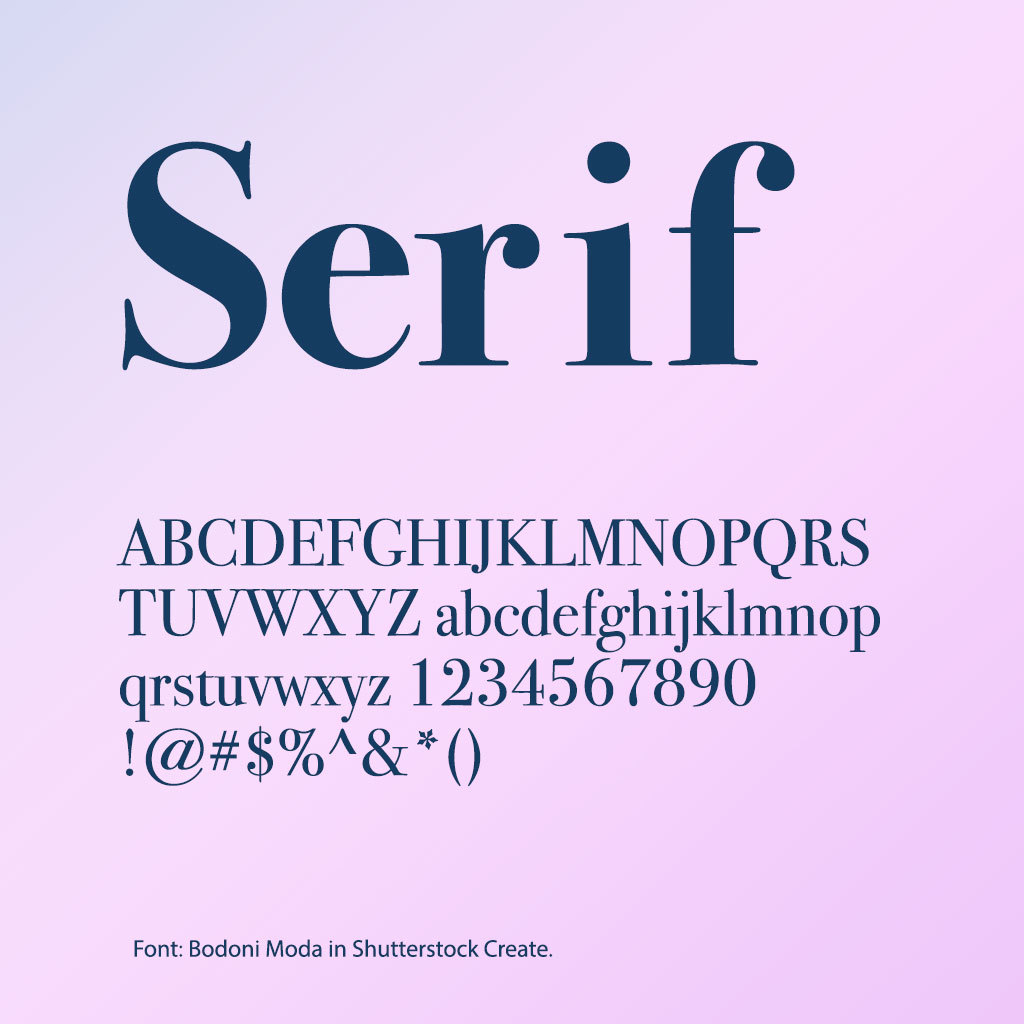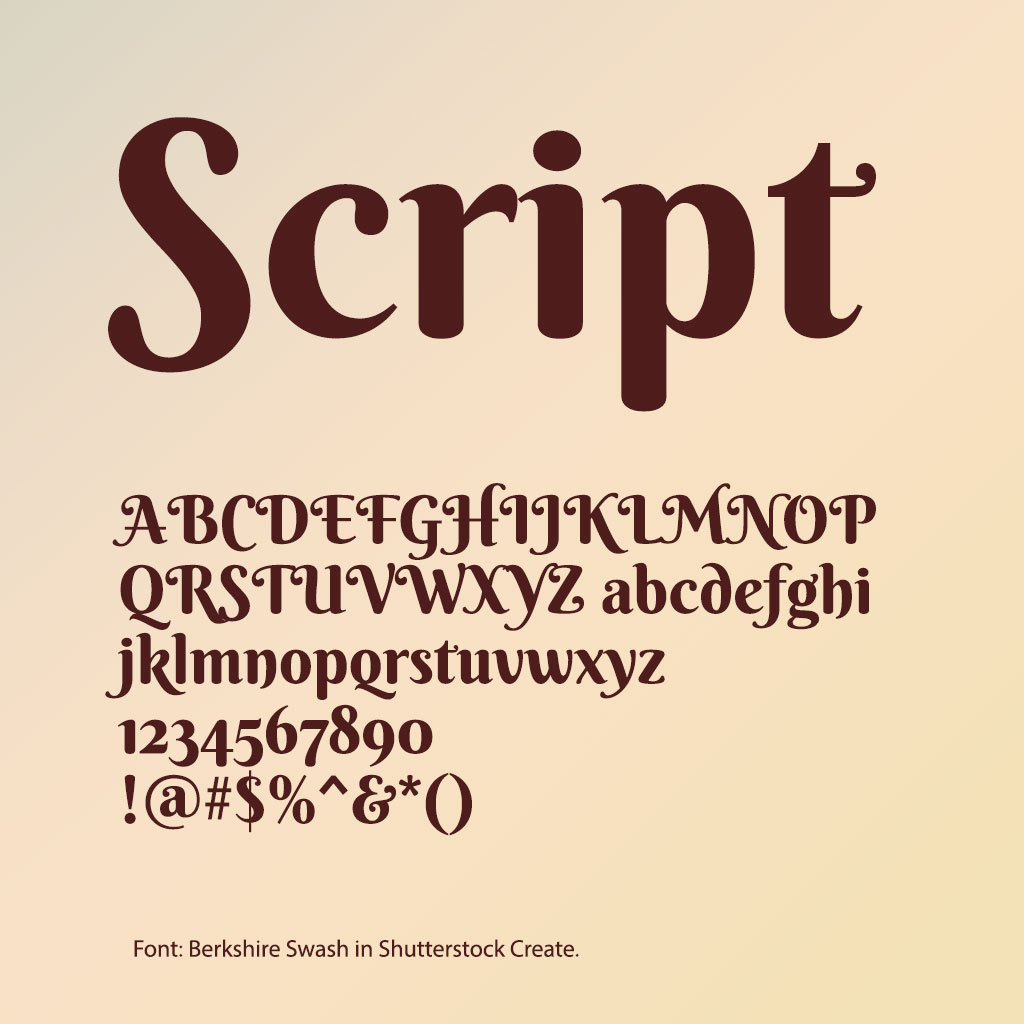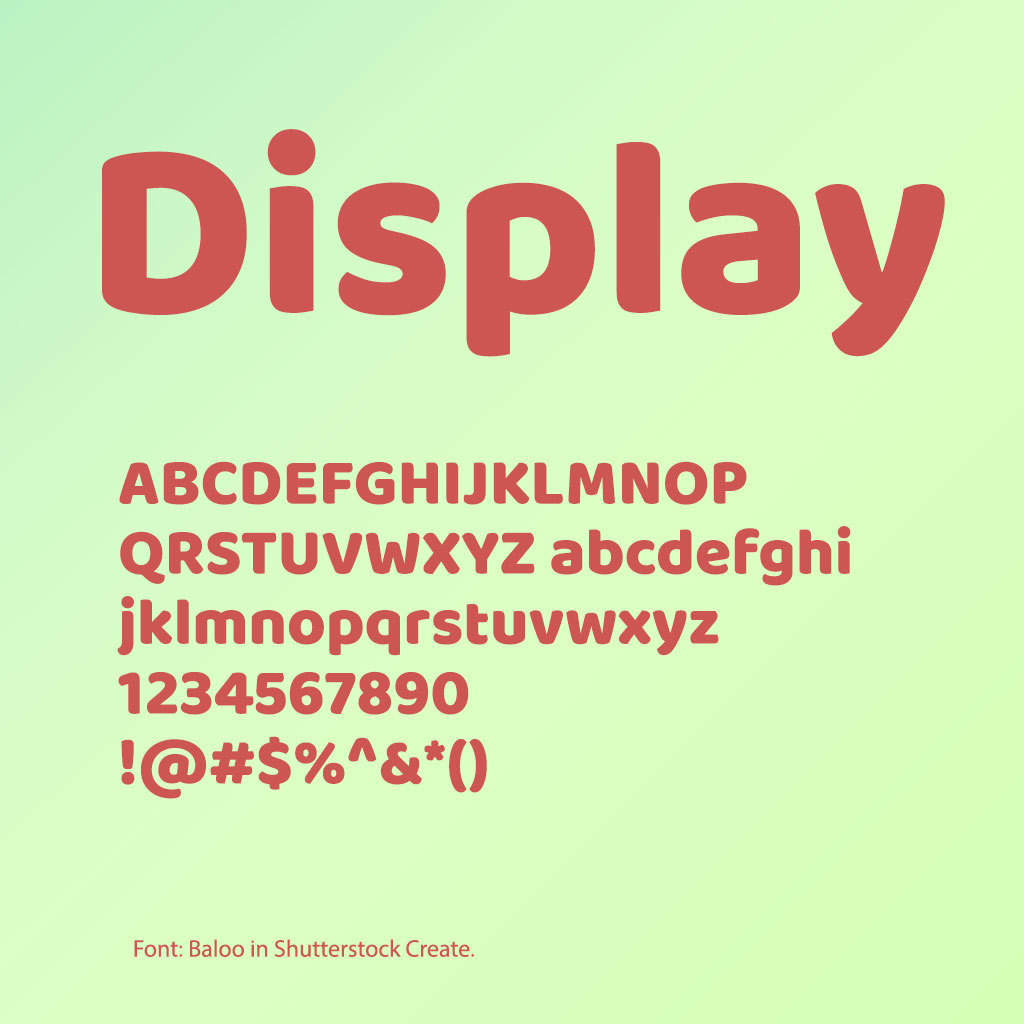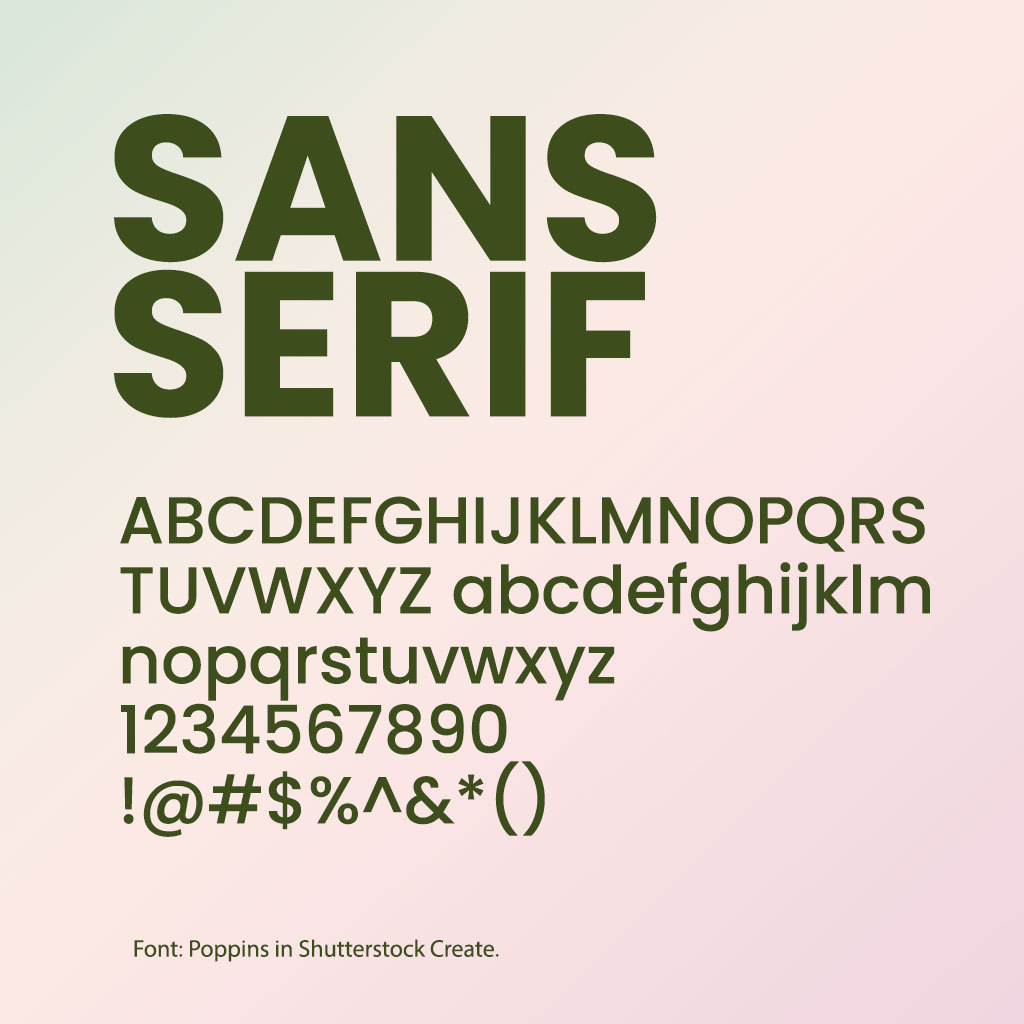
เลือกฟอนต์อย่างไรให้สื่ออารมณ์และโดนใจ
นักออกแบบมักใช้ฟอนต์ในการสร้างความรู้สึกบางอย่างให้กับแบรนด์ เช่น ความเชื่อใจ ความหรูหรา ความเป็นมิตร ฯลฯ ตัวกำหนดให้ฟอนต์มีความรู้สึกขึ้นมาก็คือสิ่งที่เรียกว่าจิตวิทยาฟอนต์ (Font psychology) มันคืออะไรนั้นมาทำความรู้จักกันเลย
ทุกอย่างรอบตัวสามารถปลุกความรู้สึกในตัวคุณได้ ทุกๆสิ่งที่รายล้อมคุณต้องการให้คุณรู้สึกอะไรบางอย่างเมื่อได้สัมผัส ซึ่งเป็นเรื่องที่นักออกแบบส่วนใหญ่รู้กันอยู่แล้ว
เคยสงสัยกันไหมว่าทำไมแบรนด์อย่าง Gucci, Prada และ Roll-Royce ถึงดูแพงและน่าเชื่อถือ ทำไมแบรนด์ Apple, Gymshark และ Nike ถึงดูมั่นใจและกล้าหาญ ทั้งหมดนี้ไม่ใช่เวทมนต์แต่เป็นหลักวิทยาศาสตร์ที่ถูกคิดมาก่อนจะสร้างแบรนด์ใดๆก็ตาม ไม่ว่าจะเป็น สี บรรจุภัณฑ์ การใช้ภาษา ฟอนต์ เป็นต้น
โดยสรุปคือนักออกแบบทุกคนต้องการให้คุณรู้สึกกับการออกแบบของเขา ในแบบที่พวกเขาอยากให้คุณรู้สึกเสมอ และแบบฟอนต์ที่เขาใช้ก็จะทำให้คุณรู้สึกแบบนั้น มันเป็นเรื่องของจิตวิทยาการออกแบบตัวอักษร ให้ทุกคนที่มองรู้สึกอะไรกับตัวแบรนด์นั่นเอง
กระทู้นี้เราจะมาพูดถึงความแตกต่างของฟอนต์ที่สามารถปลุกอารมณ์คุณได้ในหลากหลายอารมณ์ ว่าแล้วก็มาดูกันเลย
Serif Fonts
ฟอนต์นี้มีการตวัดที่บริเวณต้นและปลายของอักษร มักใช้ในงานข่าวหนังสือพิมพ์ แสดงให้เห็นถึงความน่าเชื่อถือและความเป็นทางการ ในอดีตสื่อสิ่งพิมพ์มักใช้ฟอนต์นี้อย่างแพร่หลายเพราะง่ายต่อการอ่านจากซ้ายไปขวา ฟอนต์ในตระกูลที่เกี่ยวข้องคือ
• Kotta One
• Bodoni Moda
• Didonesque
• Grenze
• Cinzel
Sans-Serif Fonts
เป็นฟอนต์ที่ดูมินิมอล สดใสและตรงไปตรงมา ส่วนมากใช้ในยุคปัจจุบันในอุตสาหกรรรมเทคโนโลยี ให้ความรู้สึกเท่ โฉบเฉี่ยวและสะอาดน่ามอง ถ้าคุณต้องการให้คนมองว่าแบรนด์คุณนั้นก้าวหน้า ฟอนต์ในตระกูลที่เกี่ยวข้องคือ
• Lato
• Montserrat
• Noto Sans
• Poppins
• Arial
Script Fonts
ฟอนต์นี้จะแสดงให้เห็นถึงความคราฟของลายมือแบบดั้งเดิม คล้ายๆกับการตวัดพู่กันด้วยมือ เหมาะกับใช้ในงานแฟชั่น เครื่องดื่มและผลิตภัณฑ์สำหรับเด็ก ฟอนต์ในตระกูลที่เกี่ยวข้องคือ
• Berkshire Swash
• Lobster Two
• Parisienne
• Northwell
• MonteCarlo
Display Fonts
นี่คือฟอนต์ที่มีพลังในการดึงดูดสายตา สามารถนำไปผสมผสานกับฟอนต์อื่นได้อย่างลงตัว แต่มักไม่ถูกใช้กับตำแหน่งที่ฟอนต์ต้องตัวเล็ก นิยมใช้แบบขนาดใหญ่เท่านั้น เหมาะกับสินค้าเฟรนด์ลี่ เป็นมิตร อยากได้ความแตกต่าง
• Anton
• Baloo
• Norwester
• Ultra
• Mergim
ฟอนต์ที่ใช่ช่วยยกระดับแบรนด์คุณได้
ฟอนต์สามารถปลุกพลังแห่งอารมณ์ที่ยิ่งใหญ่ มีหลักการจิตวิทยามากมายรองรับ ถ้าคุณต้องการเลือกฟอนต์มาใช้งานให้ลองถามตัวเองว่า
• จุดยืนของแบรนด์คืออะไร?
• คู่แข่งคุณเป็นอย่างไร อะไรทำให้คุณเด่นกว่า?
• อยากให้ลูกค้าเห็นแบรนด์คุณแล้วรู้สึกอย่างไร?
ถ้าคุณตอบคำถามนี้ได้ คุณก็จะพบฟอนต์ที่ถูกใจของคุณได้อย่างแน่นอน!